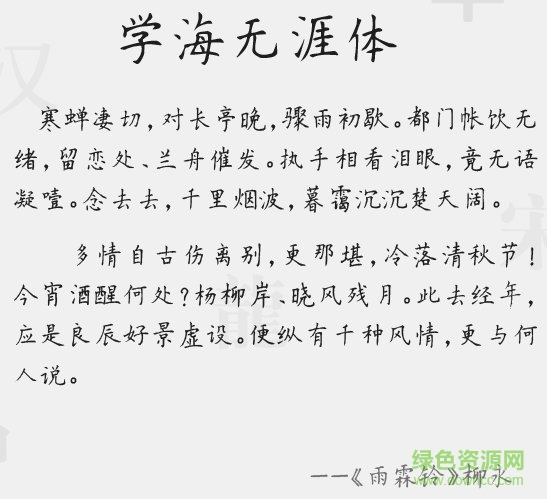
學海無涯體是一款與書山有路同源的硬筆手寫字體,字跡硬朗有形,自帶加黑讓文字更加深入人心,喜歡的朋友就來綠色資源網(wǎng)體驗吧!
學海無涯體育書山有路體均屬于硬筆手寫書法字體,字跡利落爽快,有著極其出色的藝術(shù)魅力,可以廣泛使用在藝術(shù)設(shè)計、平面設(shè)計等諸多領(lǐng)域當中!